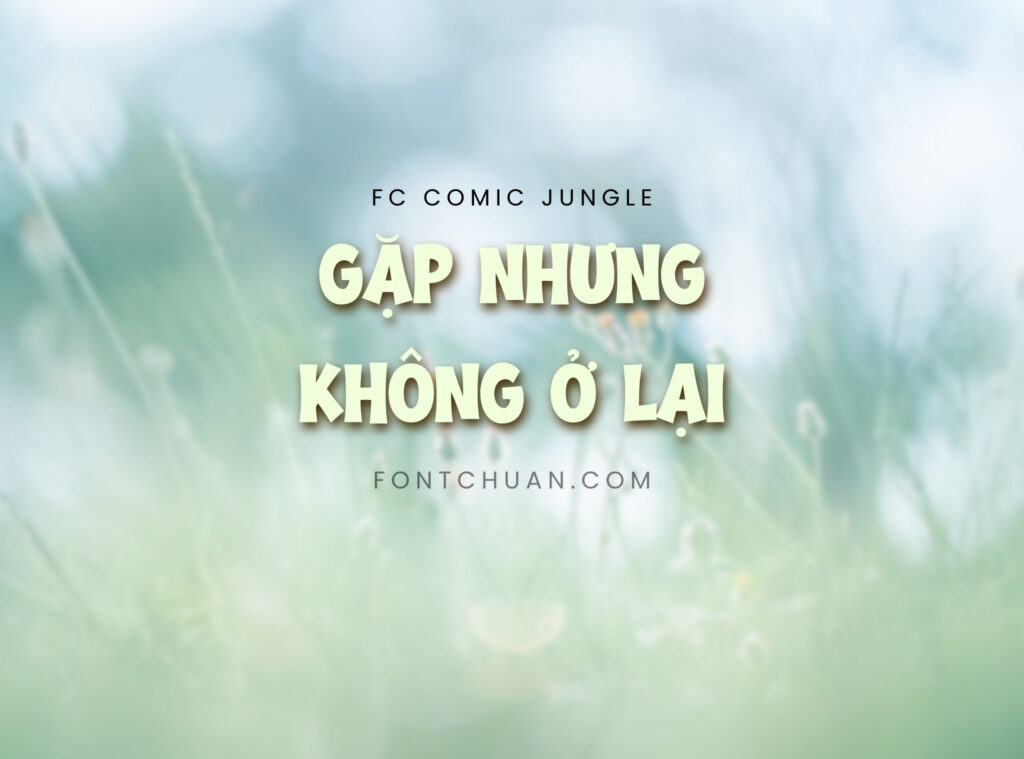
Font FC Comic Jungle Việt Hóa
Comic Jungle là một font chữ mang phong cách hoạt hình vui nhộn, được thiết kế bởi Blankids Studio. Font này bao gồm hai kiểu chữ: Regular và Extrude, với đầy đủ các ký tự chữ hoa, chữ thường, số và dấu câu.
Về thiết kế, FC Comic Jungle sở hữu các đường nét đậm, góc cạnh mềm mại và cấu trúc chữ cân đối, tạo nên sự hài hòa và dễ đọc. Font này lý tưởng cho các thiết kế liên quan đến ngành ẩm thực, ăn uống, bao bì, trẻ em, giải trí, sự kiện và các ấn phẩm quảng cáo khác. Ngoài ra, FC Comic Jungle cũng là lựa chọn tuyệt vời cho các dự án font chữ Tết hoặc font chữ Giáng Sinh, như thiệp mừng năm mới, banner lễ hội, trang trí noel, mang đến không khí vui tươi, ấm áp và phù hợp với tinh thần lễ hội.